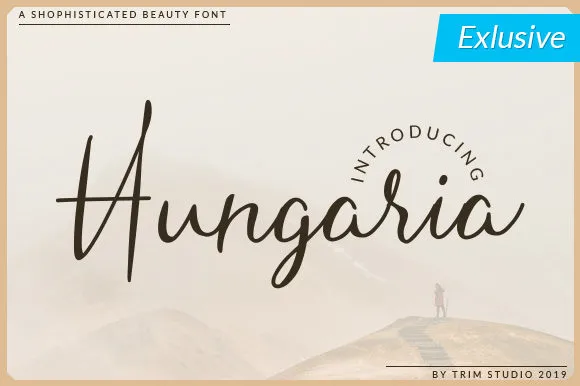
Hungaria Script Font – Fonte Grátis
Hungaria Script Font
A Hungária Script Font é uma elegante escolha para designers que procuram adicionar um toque refinado a seus trabalhos. Criada pelo designer Trim Studio, essa fonte script não apenas oferece beleza e feminilidade, mas também traz uma sensação única de sofisticação. Ideal para marcas que desejam expressar elegância em suas campanhas ou embalagens, é perfeita para design gráfico que busca personalizar com delicadeza e profissionalismo. Esta fonte é um complemento ideal tanto para elementos visuais de moda quanto para designs de logotipos femininos, garantindo uma presença única e atraente em qualquer projeto onde seja usada.